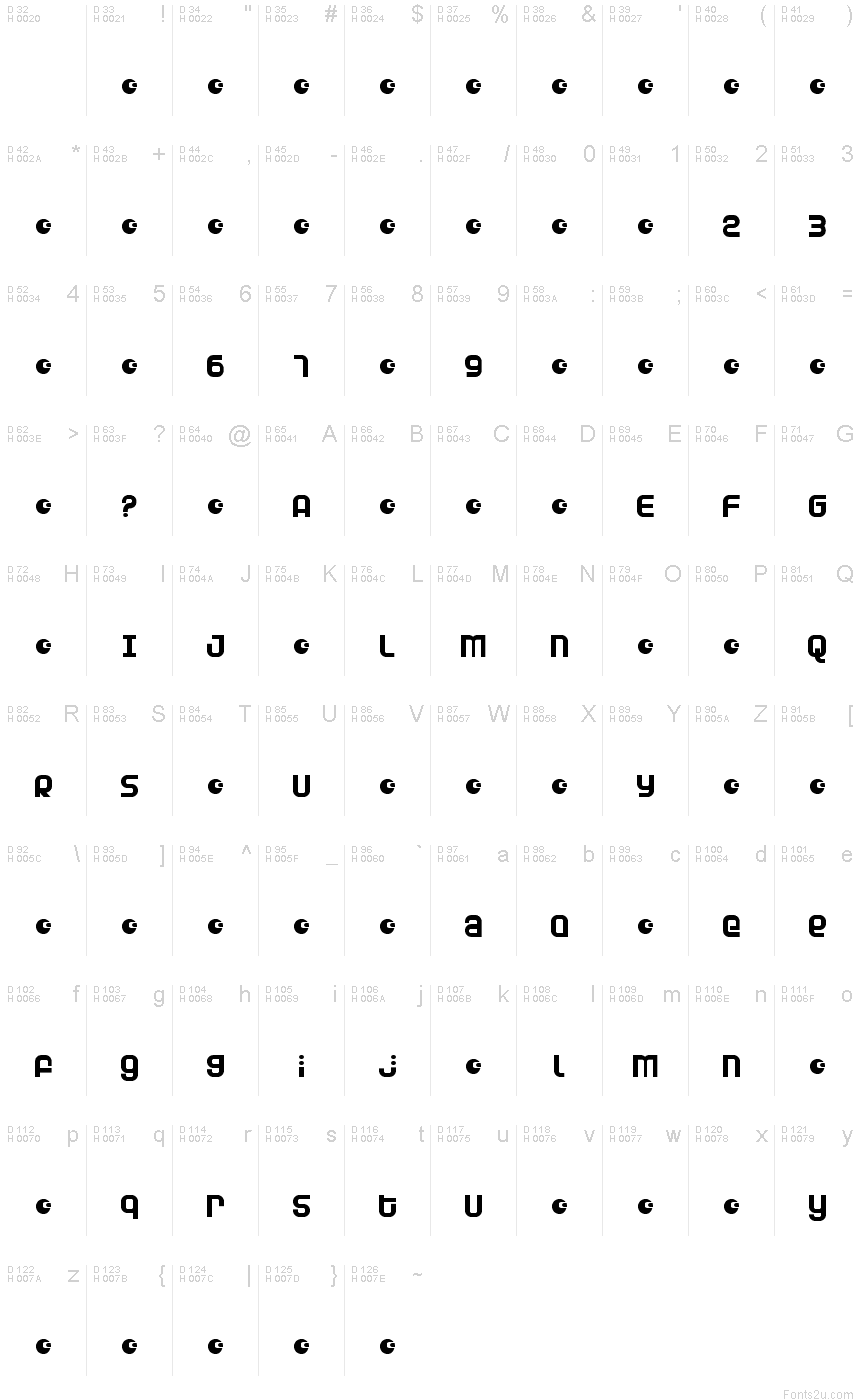
Dunebug Alternates od Fontalicious Fonts to nowoczesny, darmowy krój pisma typu display. Jego masywne kształty o łagodnych narożnikach i modularne krzywizny nadają każdemu słowu wygładzony, zabawkowy, technologiczny charakter, sprawiając wrażenie, jakby każda litera została odlana z błyszczącego plastiku. Dzięki alternatywnym znakom możesz przełączać się między kwadratowymi a bardziej otwartymi sylwetkami, więc wystarczy kilka zmian, aby logo lub nagłówek nabrały przyjaznego lub futurystycznego wyglądu.
Dunebug Alternates zapewnia odważny, czytelny efekt w logach gier, plakatach sci-fi, ekranach powitalnych aplikacji, opakowaniach produktów, ulotkach i brandingach w stylu retro-futurystycznym. Ten darmowy font najlepiej prezentuje się w dużym rozmiarze z dużymi odstępami, które pozwalają tym zaokrąglonym blokom „oddychać”. W tekście głównym połącz Dunebug Alternates z prostym, geometrycznym krojem bezszeryfowym o mniejszej grubości, aby zachować odpowiednie skupienie energii wizualnej.